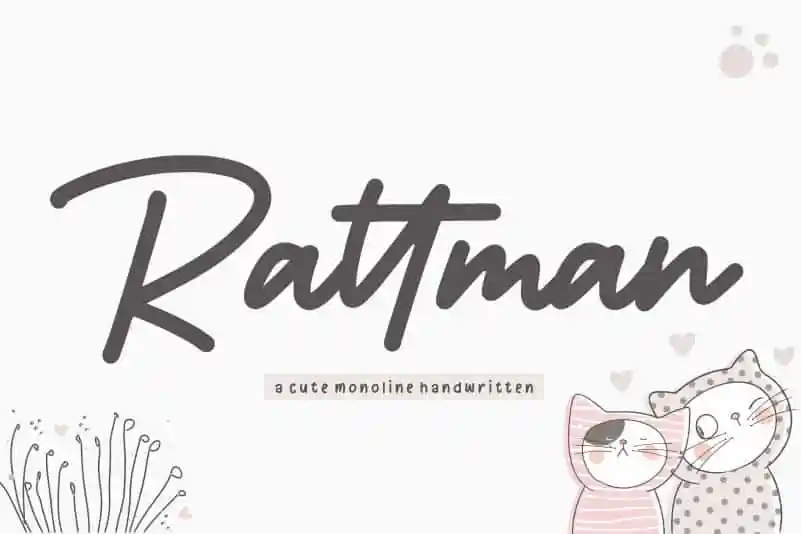
Rattman Monoline Handwritten Font – Download Grátis
A Rattman Monoline Handwritten Font é a escolha perfeita para quem busca uma fonte que expressa charme e sofisticação sem perder sua elegância natural. Com seu traço sólido e linhas levemente curvadas, a Rattman se destaca em criações de marca, embalagens de produto ou até mesmo no design de jornais e revistas. Seja para criar um layout de assinatura sofisticada, destacar uma celebração especial como o casamento da sua vida, ou apenas para dar um toque único aos seus materiais digitais, a Rattman é ideal. Específicamente, ela está projetada para expressar texto acima do fundo, sem perder seu brilho e beleza. É perfeita para aplicação em mídias sociais, embalagens de produtos, editoriais de revistas ou até mesmo como fonte de assinatura em seus materiais de marca. Sua elegância natural, combinada com um toque sofisticado, a torna uma excelente escolha para qualquer projeto que você esteja trabalhando.